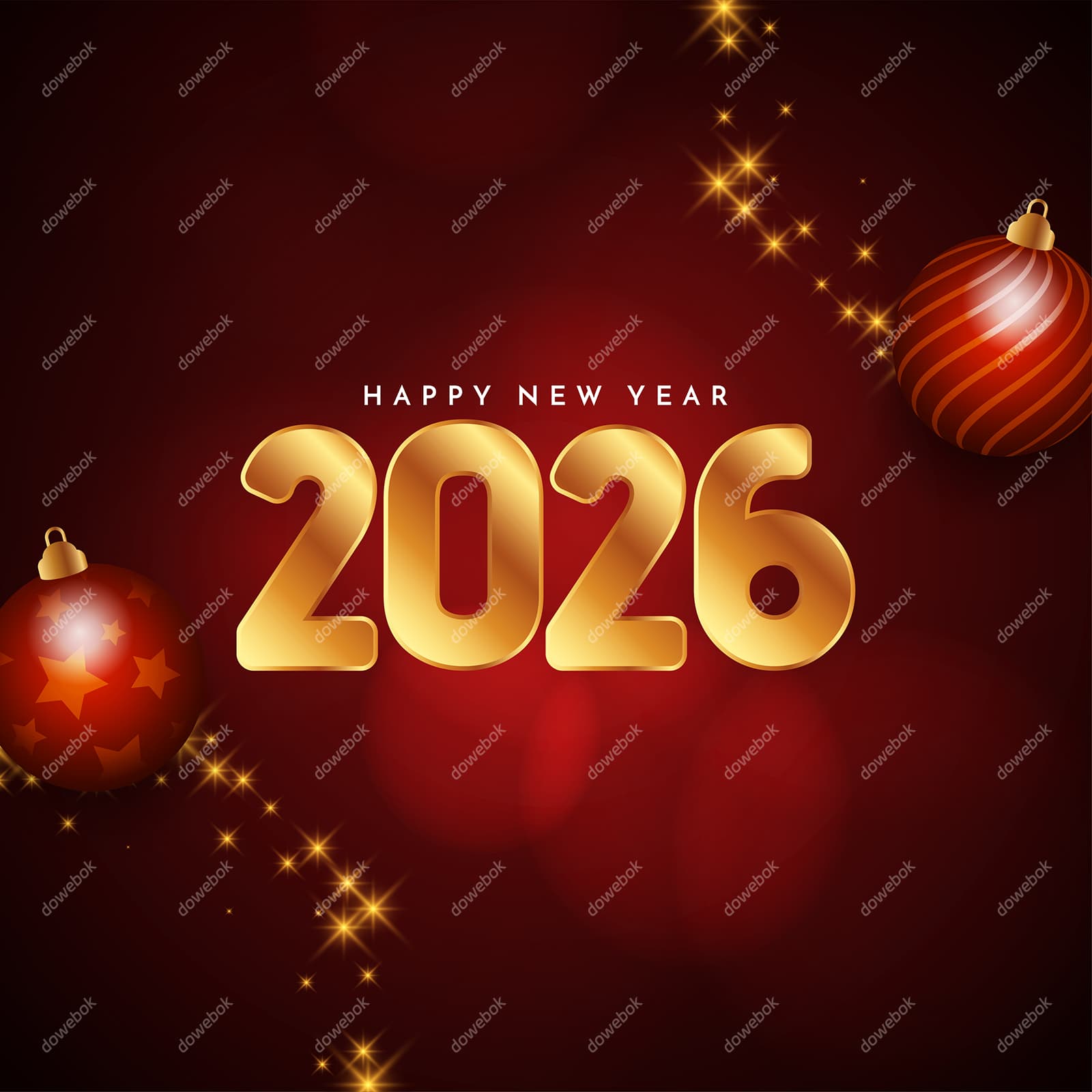
这是一款由红色圣诞球和金色数字设计的 2026 新年快乐矢量素材,深红渐变背景晕染着柔光,金色立体 “2026” 字体醒目华贵,上方配 “Happy New Year” 英文,两侧点缀红金装饰球与星芒光斑。红金配色浓郁喜庆,装饰球与星光元素既强化了新年的热烈氛围,又以精致质感传递出温馨的仪式感,适配传统新年贺卡、节日装饰物料等场景。